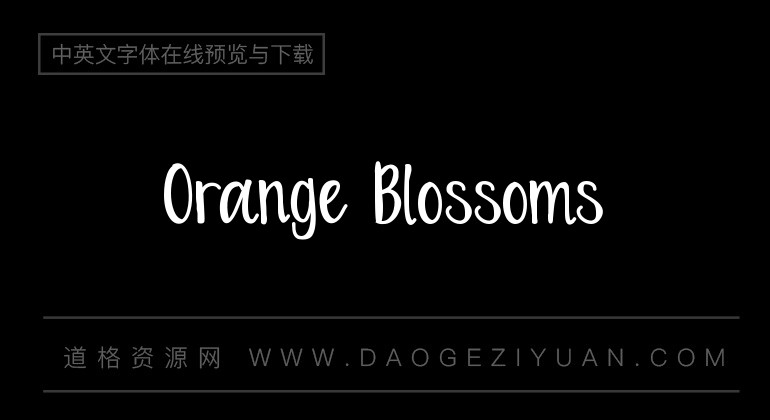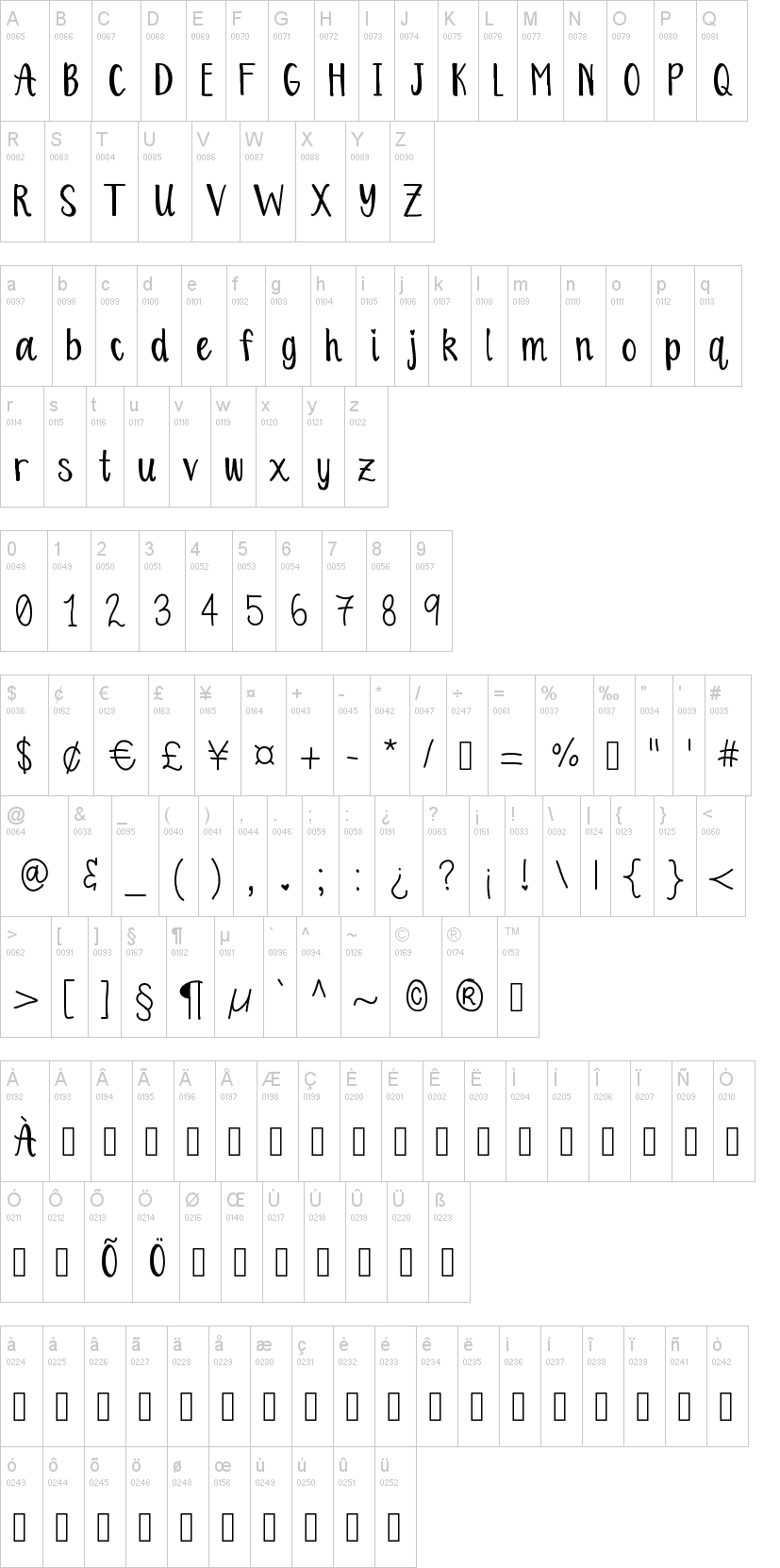
? Orange Blossoms 是一款由设计师 Laura Worthington 创作的手写体字体,它具有优雅、温柔、自然的特点。它的设计特点是拥有柔和的曲线、优美的折线、温柔的笔画,以及柔和的细节,让你的文字设计看起来更加精致。它的字形特点是拥有精致的细节,字体看起来更加优美,而且它的字体也可以更好地突出文字的特点。Orange Blossoms 字体可以用于各种印刷品,包括海报、书籍、书签、礼品卡等,它可以为你的设计增添一份浪漫的气息。内容介绍
Orange Blossoms是一款非常不错的手写艺术字体,具有很好的视觉感,适合于文化类的宣传设计、商业类品牌的广告和产品包装设计以及个性化文字排版等较多场景。